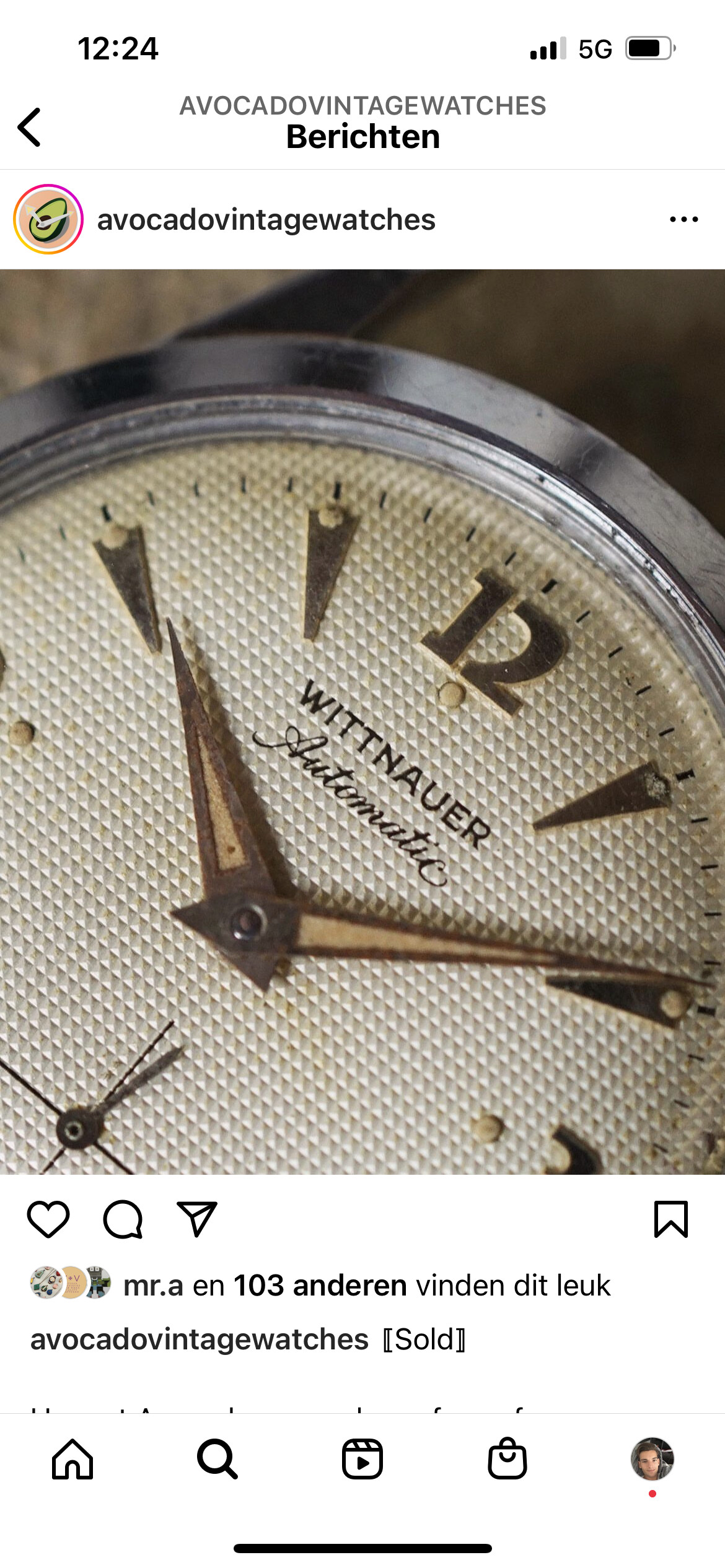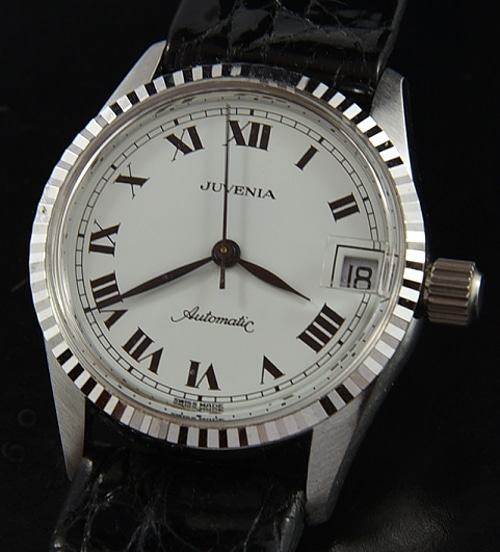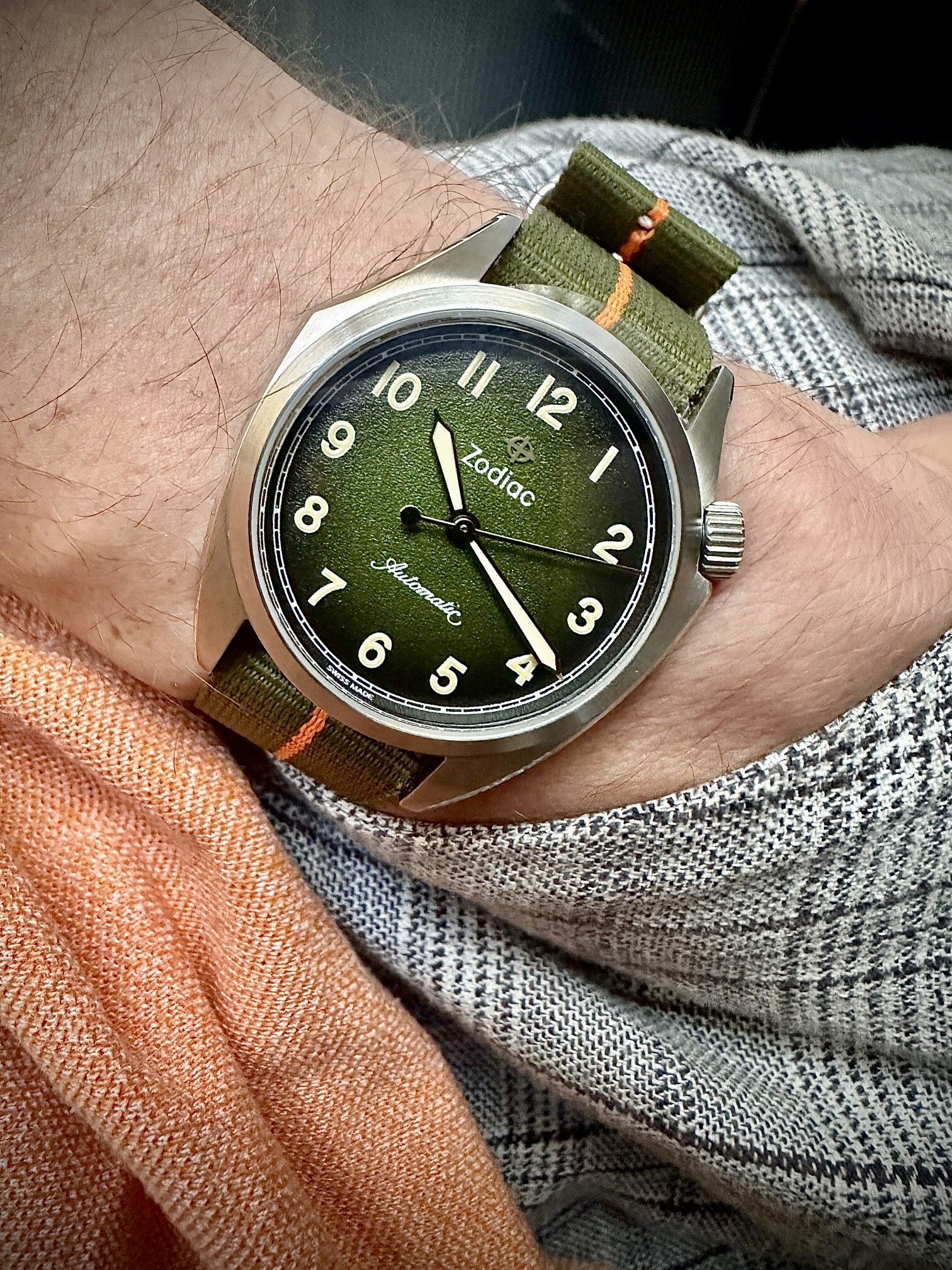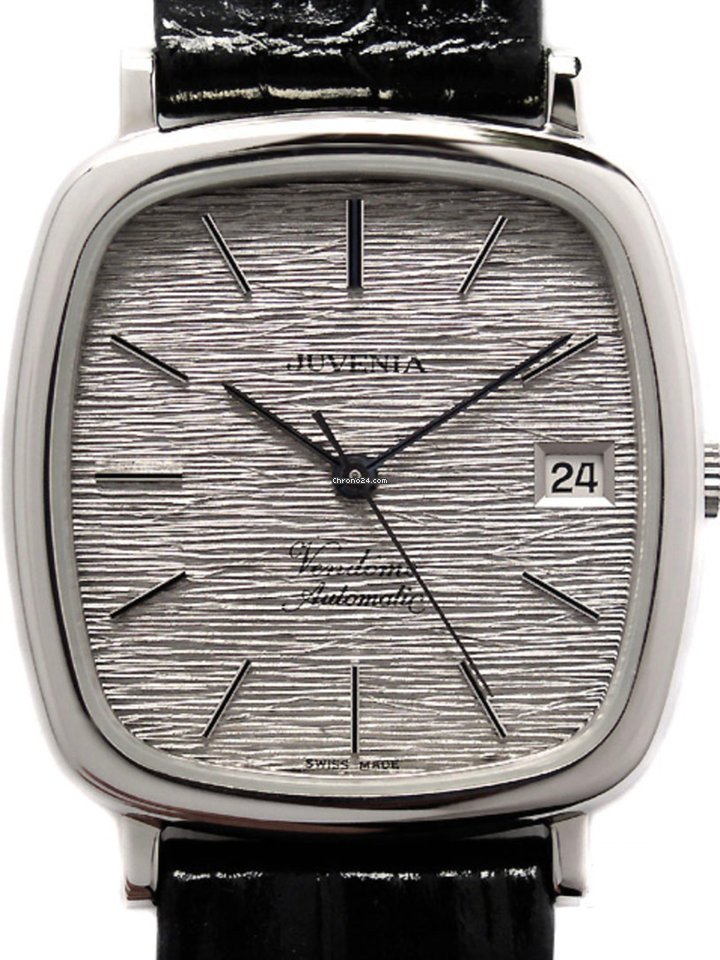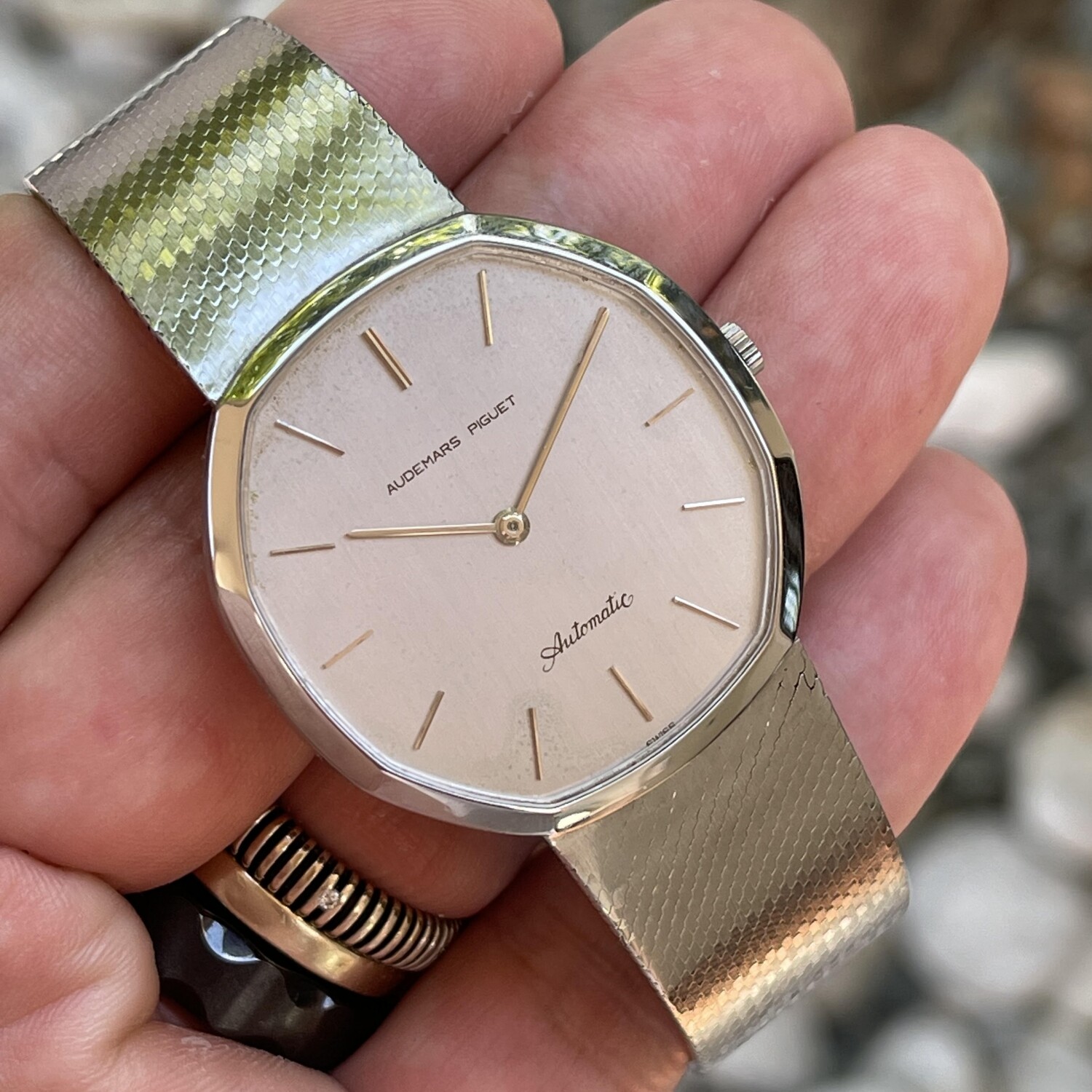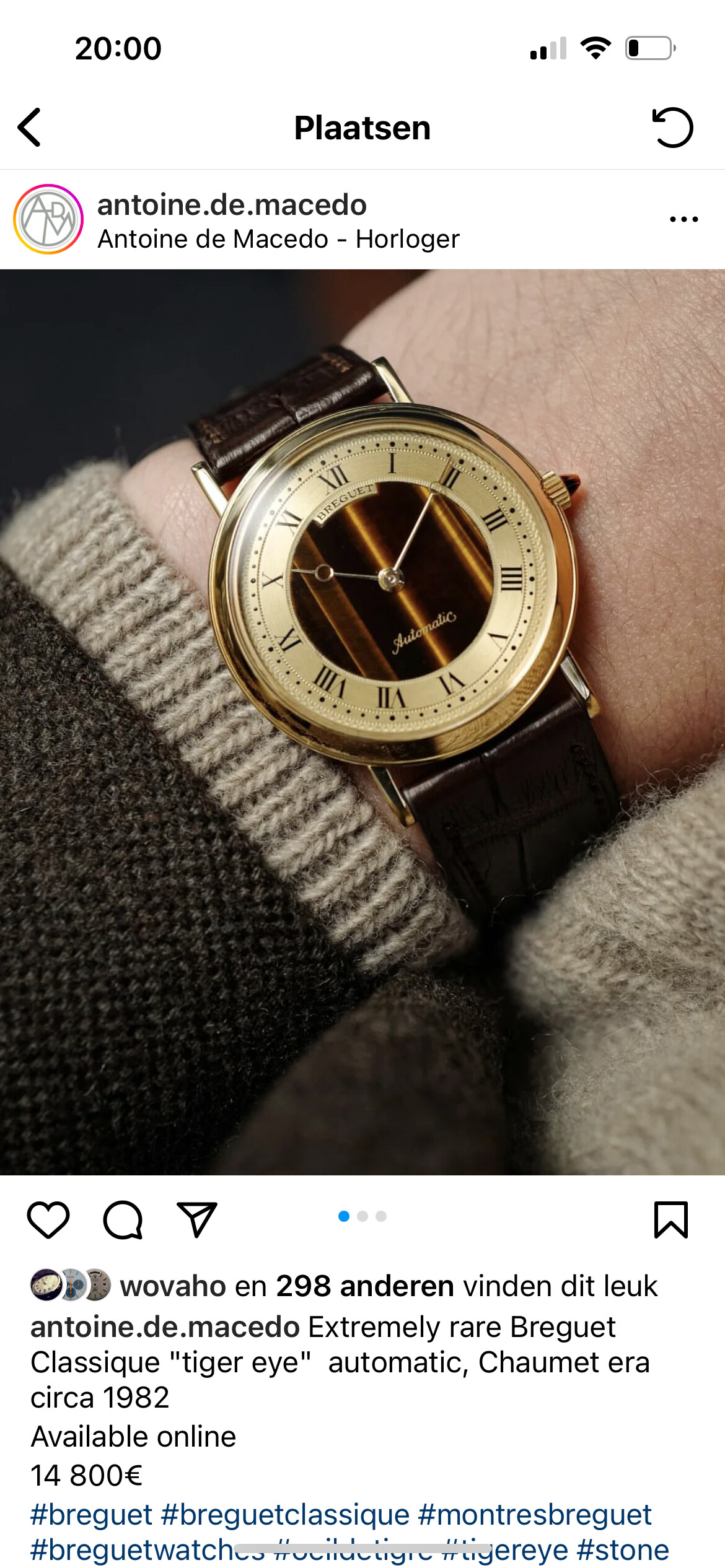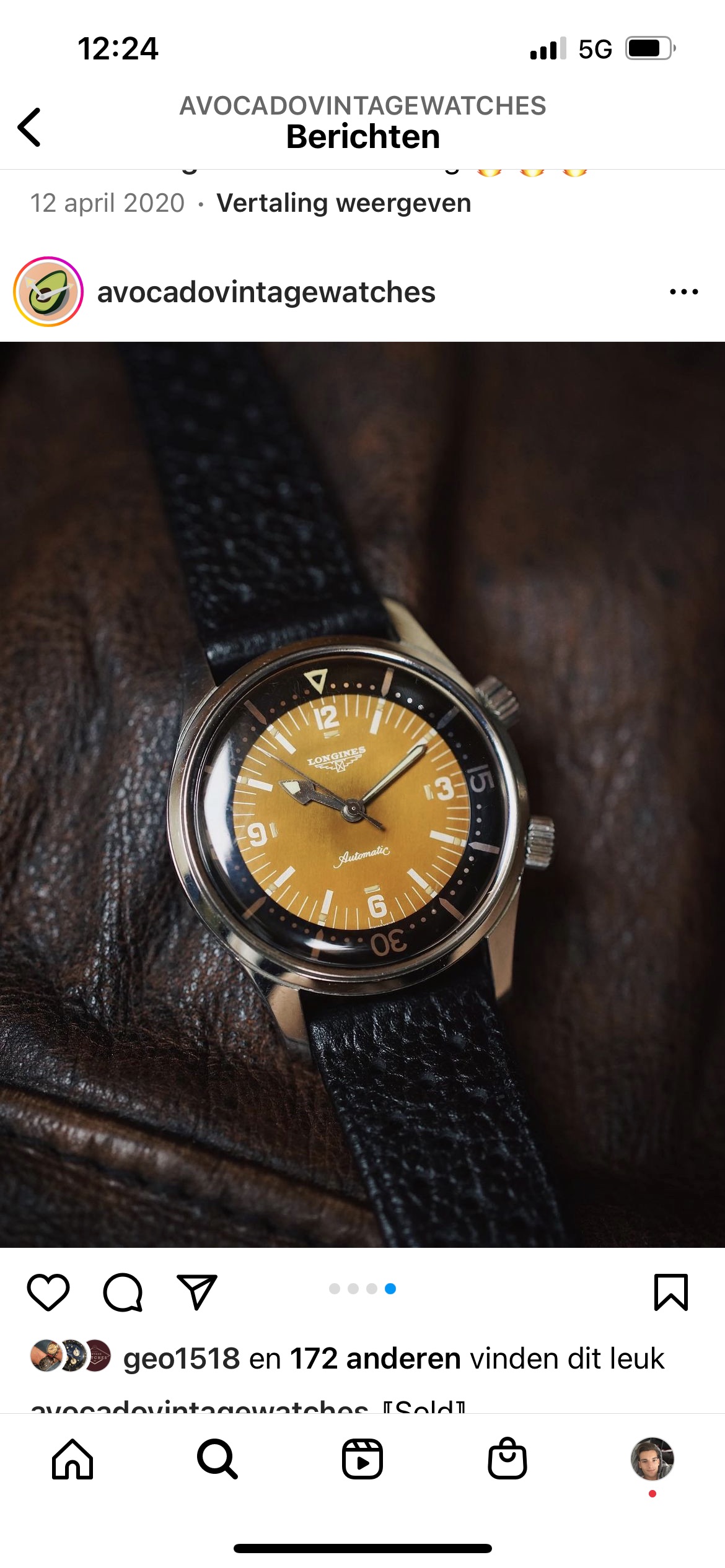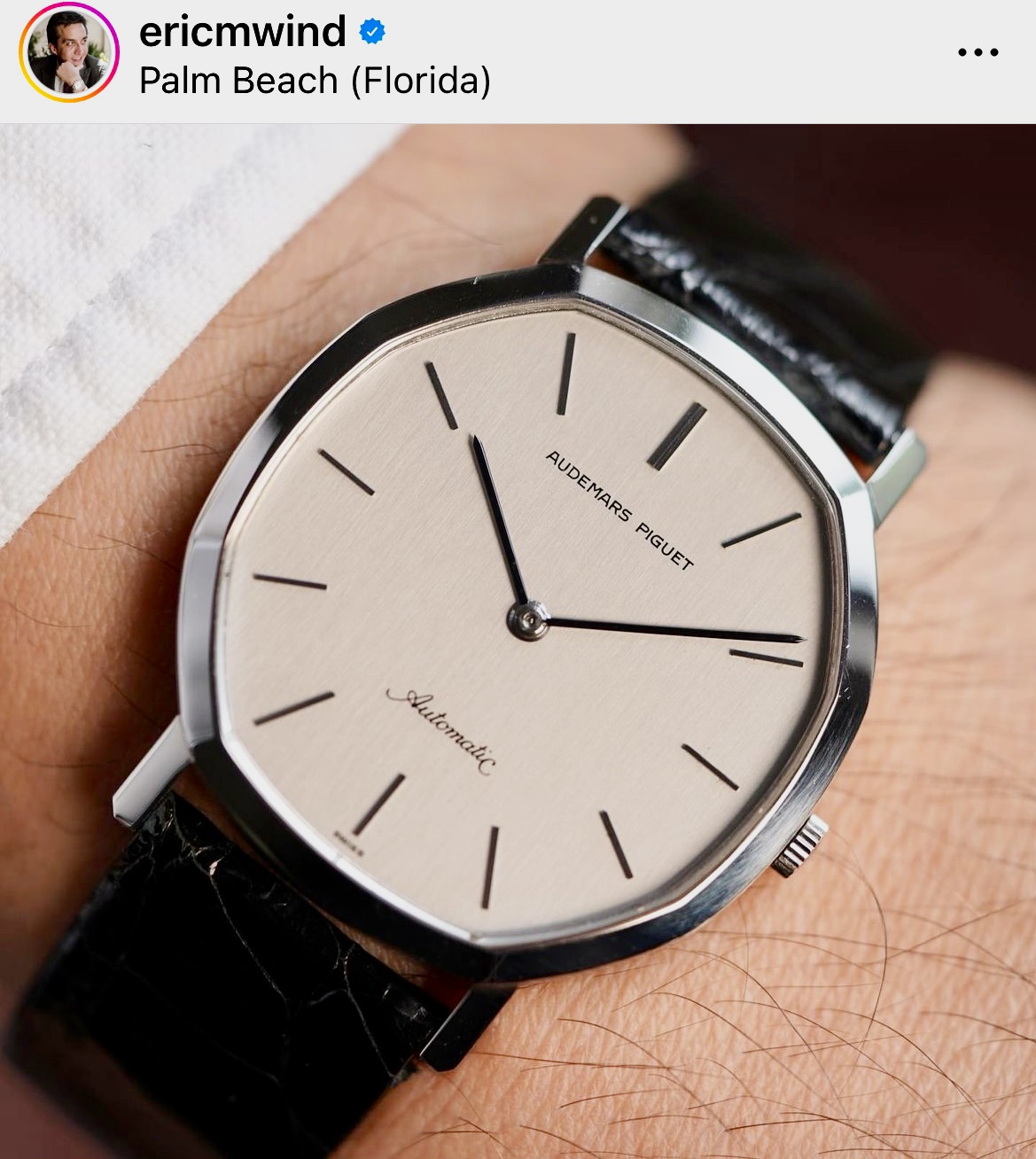
Ode aan de automatic (font)
Fonts zijn vaak een onderbelicht designelement van horloges. Mede omdat merken zelden ervoor kiezen om het een opvallend element te laten zijn. De meeste merken kiezen een font dat zo min mogelijk opvalt en ondergeschikt is aan de rest van het design.
Positieve uitzonderingen hierop vind ik met name in Duitsland bij Nomos, GO en A. Lange & Sohne
Een font dat bij mij juist altijd direct de aandacht opeist en daarmee in mijn ogen een van de mooiste ooit gebruikt is, is het ‘automatic’ font waar dit topic over gaat.
Als vintage liefhebber kom ik het geregeld tegen en mij viel met name op dat ik het font bij verschillende merken tegenkwam. Hieronder voorbeelden van Longines/Wittnauer, Bergana, van Cleef en Arpels, Juvenia en Audemars Piguet. Met name AP en Longines hebben het font op talloze modellen gebruikt.
Longines:
AP:
Overige:
Tot mijn verbazing zag ik het ook op moderne modellen voorbij komen van niemand minder dan Zodiac:
En Kurono Tokio heeft gekozen voor een net iets ander font (zie de lus van de A) met veel gelijkenis:
Ik ben heel benieuwd of er mensen nog meer merken kennen die dit font hebben gebruikt (of nog gebruiken) en of iemand meer informatie heeft over het font zelf heeft.
Aan de ene kant boeide zoiets me nooit, maar aan de andere kant. Als ik de foto’s zo zie. Vind ik het best een mooi toevoeging :ok_hand:t2:
Interessant topic! Nog nooit bij stilgestaan dat op mijn Sinn 103 st ook de tekst ‘automatik’ staat in het erg klassieke lettertype. Op vroegere modellen stond er nog het Engelse ‘automatic’.
Sinn heeft voor dit model heel duidelijk de mosterd gehaald bij de Breguet Type XX uit de jaren zestig, en het logo van Breguet komt wel erg overeen met het lettertype van ‘automatic’.
Breguet heeft in de horloge-geschiedenis wel een belangrijke positie, en dat bracht me bij het volgende interessante artikel over lettertypes. Misschien geen antwoord op je vraag, maar wel leuk leesvoer :slightly_smiling_face:
Dus ook Breguet
Maar Eterna ook toch dacht ik, maar hun ‘Centenaire’ lijkt er alleen maar bedrieglijk veel op, net als sommige Memomatic uitvoeringen van Pontiac.
Ebel doet ook mee. Hier weet je dat het horloge, mits voorzien van het sierlijke automatic, een el Primero hart heeft.
Ik weet dat Kuenstler Script wel die typische A gebruikt :point_down:
Verder zou je kunnen zoeken op Script fonts op de Linotype website.
Zullen er vast nog wel een paar honderd zijn die er zo uitzien…
De A klopt, de C is beduidend minder sierlijk. Het font van de Ebel komt meer overeen met dat van de Kurono Tokio.
Foto van mijn El Primero, gewoon omdat hij zo mooi is.
Seiko doet het ook!
Ook GP kan aan het lijstje van merken worden toegevoegd
Niet Automatic maar Powermatic 80
Met sierlijke letters en aparte P.
Gek genoeg, de meeste budget horloges hebben de Automatic font op orde.
• Juist de upscale brands don’t invest enough in that font
Leuke Aut-O-Matic fontindeling, @Pseikopaat, Mark! :+1::heart::sunglasses: